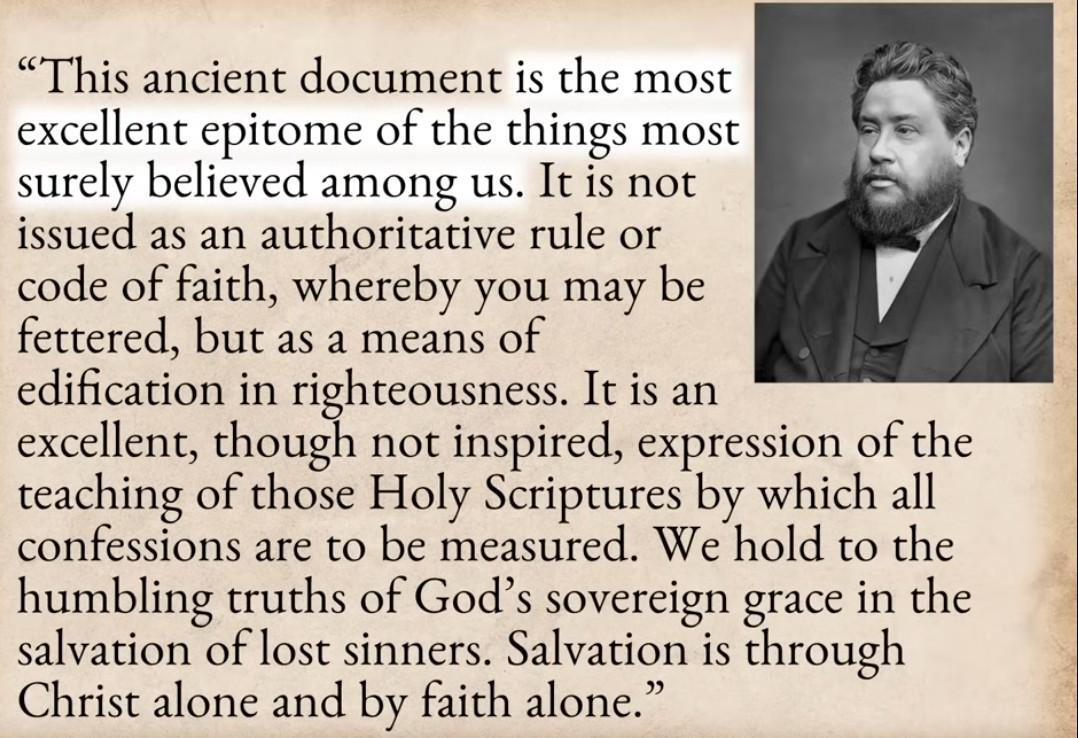
Suche Schrift aus konfessionskundlichem Video (von »Ready to Harvest«)
Der angehängte Screenshot-Ausschnitt ist aus dem Video
Ich wüsste gern, welche Schriftart (möglichst genau) verwendet wurde, unabhängig von Lizenzform oder Kosten.
Der Ersteller passt seine Schriftarten oft dem Thema an; m.E. hat er es hier besonders gut getroffen.
Ich tippe auf die EB Garamond.
Sieht schon sehr danach aus, danke.
Die hatte ich nicht mehr auf dem Radar, weil andere z.T. auch freie Fonts mittlerweile »mehr können«, was Opentype-Features angeht, und ich mich länger nicht mehr mit ihr beschäftigt habe. Aber in dem, was sie gut kann, ist sie m.E. wunderschön.